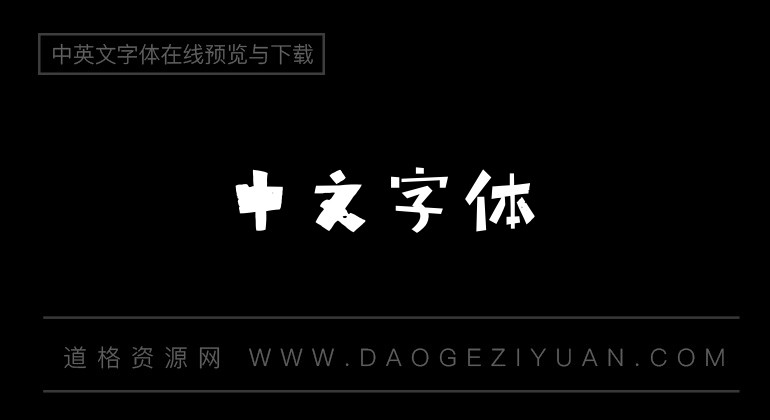
海派腔调艺术粗黑简1.0字体是一款拥有海派腔调艺术特色的汉字字体,字形粗犷大气,结构严谨,笔画粗细均匀,笔画粗细比例精致,字体英文字母清晰,细节处理精良,给人一种沉稳、大气、厚重的感觉,适合用于海派腔调艺术设计。文件名:HaiPaiQiangDiaoYiShuCuHeiJian1-0-1.ttf
海派腔调艺术粗黑简1.0是一款非常不错的手写艺术字体,具有很好的视觉感,适合于文化类的宣传设计、商业类品牌的广告和产品包装设计以及个性化文字排版等较多场景。